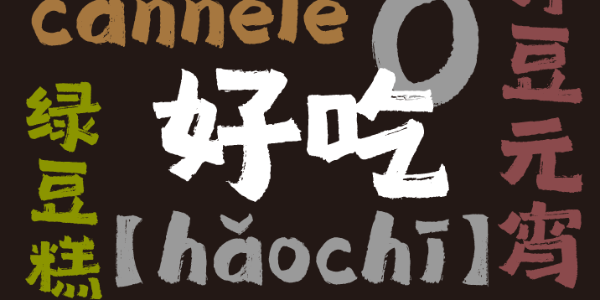
盘不了国宝,就盘它~
汉仪熊猫体是一款承载了蜀文化的书写字体,以写意的手法使得熊猫形象跃然纸上,无需具象的细节描绘,凭借书写的笔法和状态令人联想到憨态可掬的川地熊猫、茂密清幽的竹林云海、烟雾缭绕的火锅小吃和悠闲轻松的蜀人生活哲学。作为一款寓巧于拙的书写标题字体,适合应用于影视娱乐、休闲文旅、食品餐饮、书籍绘本、展览广告等使用场景,渲染自然的生命力和生活的烟火气。汉仪熊猫体的书写不止于字体,有着更广大的愿景:那就是成为四川的文字符号和字体印象。
熊猫的憨厚、蜀人的安逸、四川的文脉,都在字里了。
字形取熊猫圆满丰腴的造型,坐、立、滚、爬,形态各异,变化丰富。
笔画圆转灵动,头圆尾短,浑圆饱满。
布白均匀且自然,小而灵动的笔画点缀其中,生动可爱。
书写于宣纸之上,墨水晕染出毛边。
西文部分的书写同样轻松圆转,笔墨生动,使得熊猫的形象跃然纸上,栩栩如生,中西文匹配和谐自然。